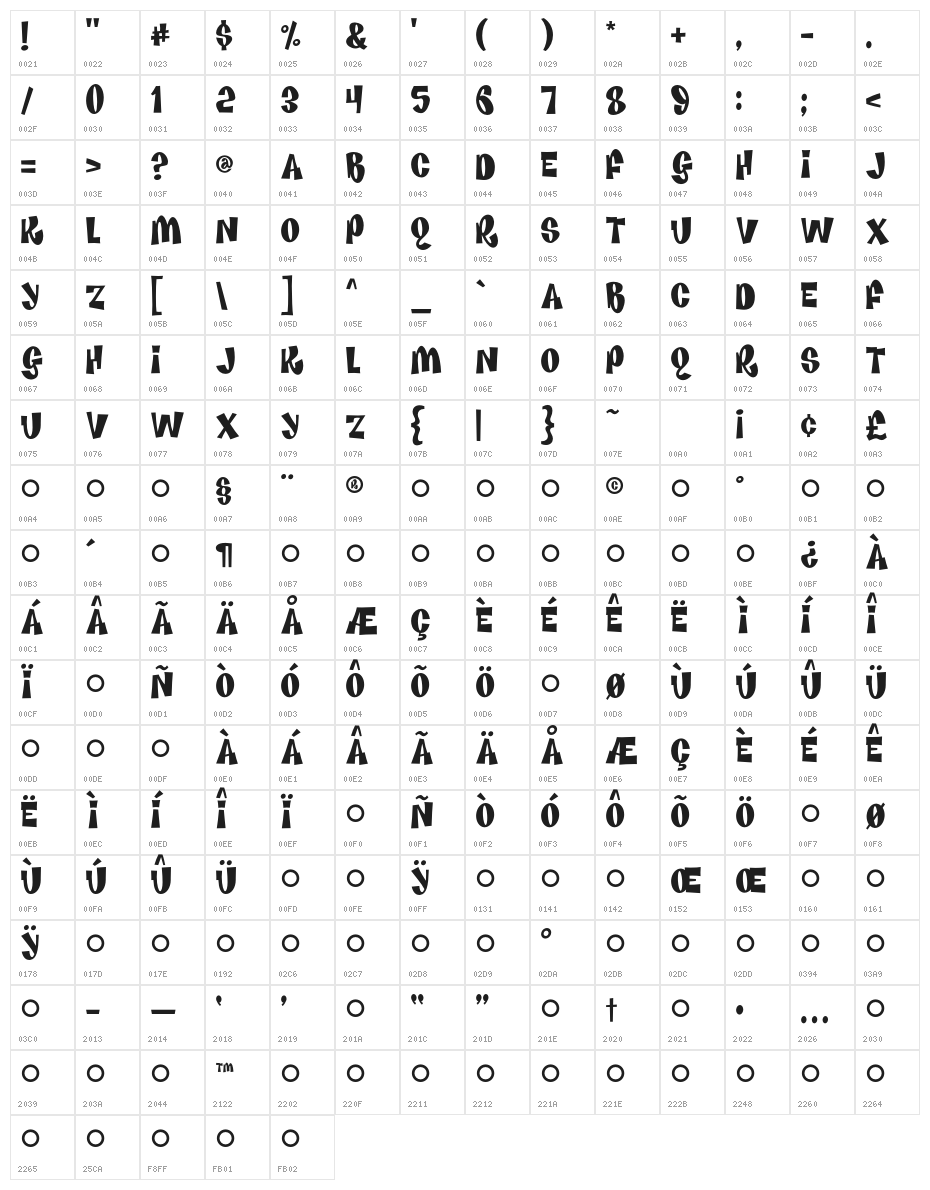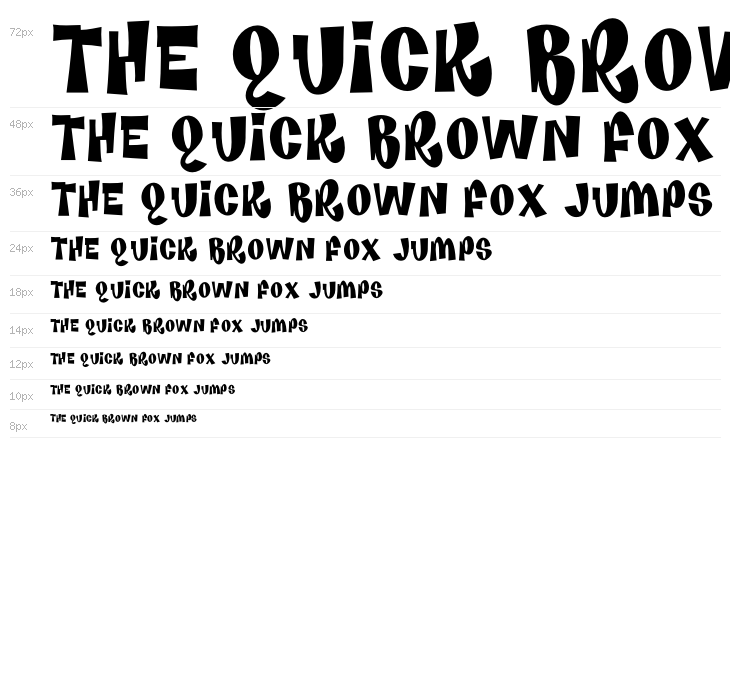
Funkhouse Font
| समग्र शैली | Playful, Whimsical |
| उपयोग का मामला | Headlines, Logos, Posters |
| सुझाए गए प्रोजेक्ट | Ideal for children's books, playful branding, event posters, and creative advertisements. |